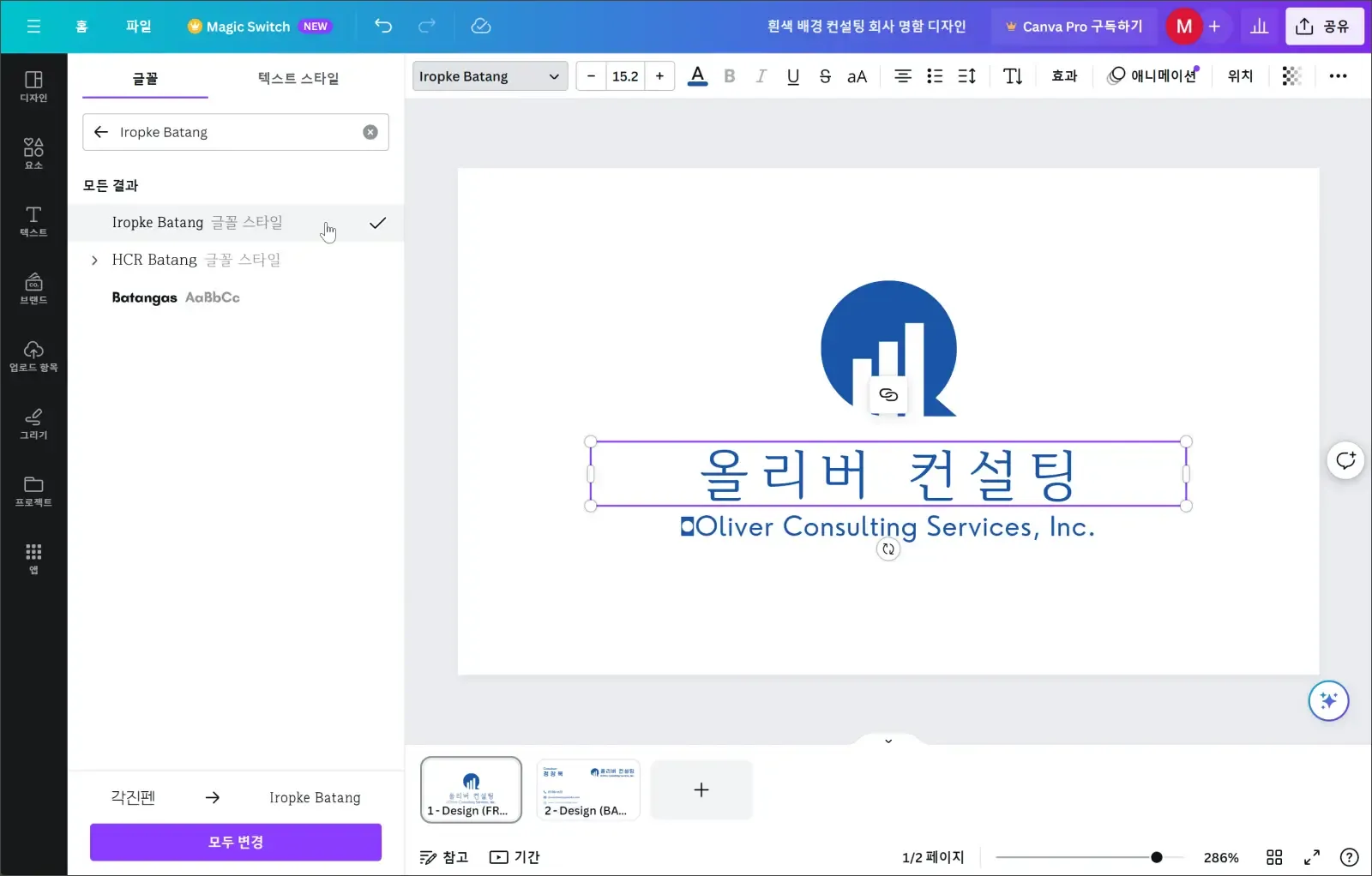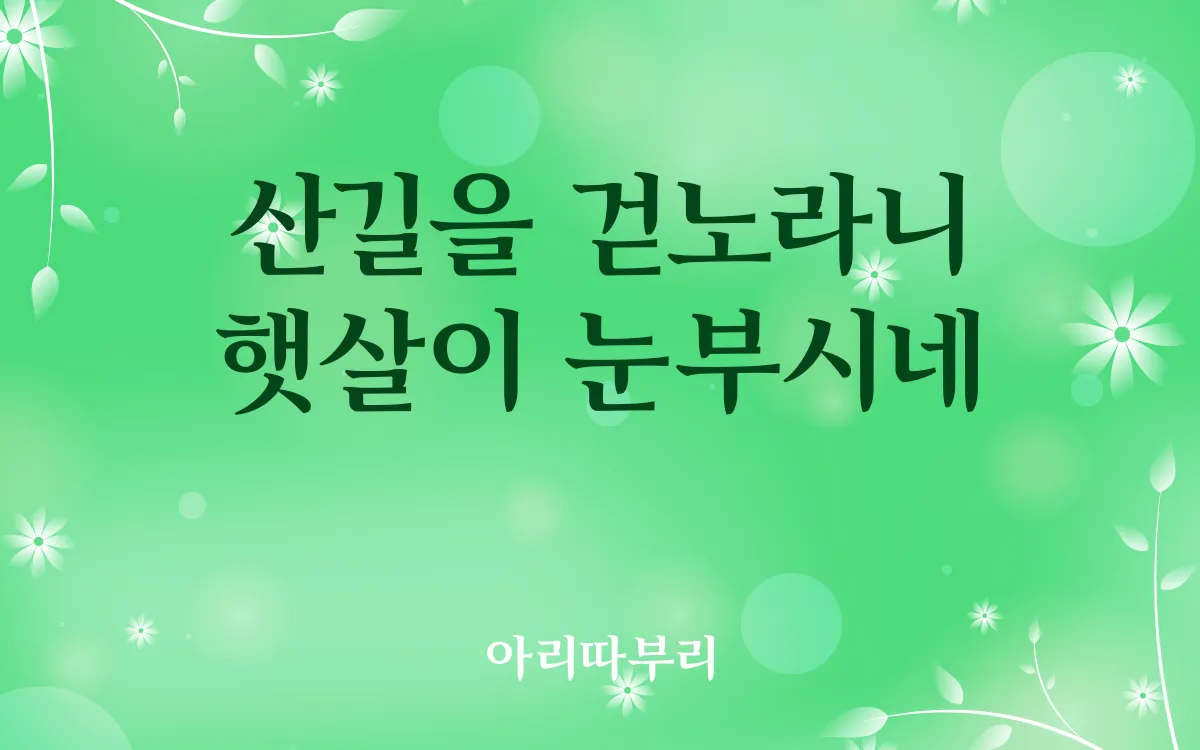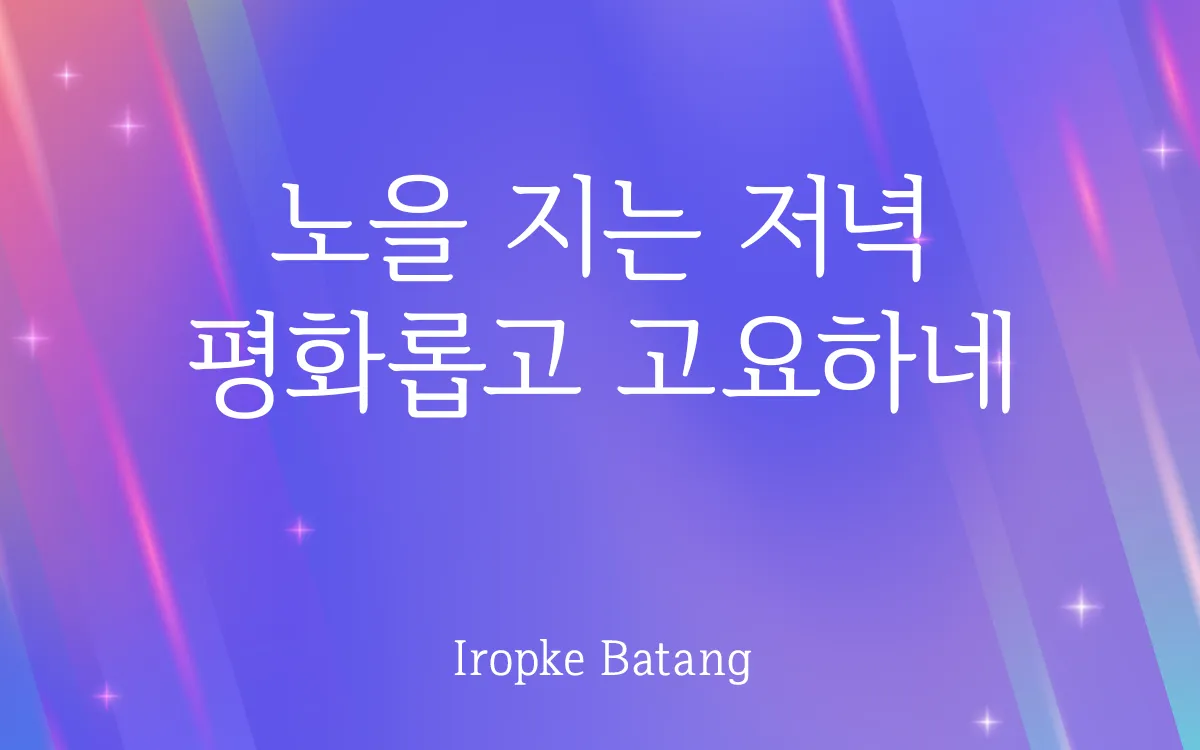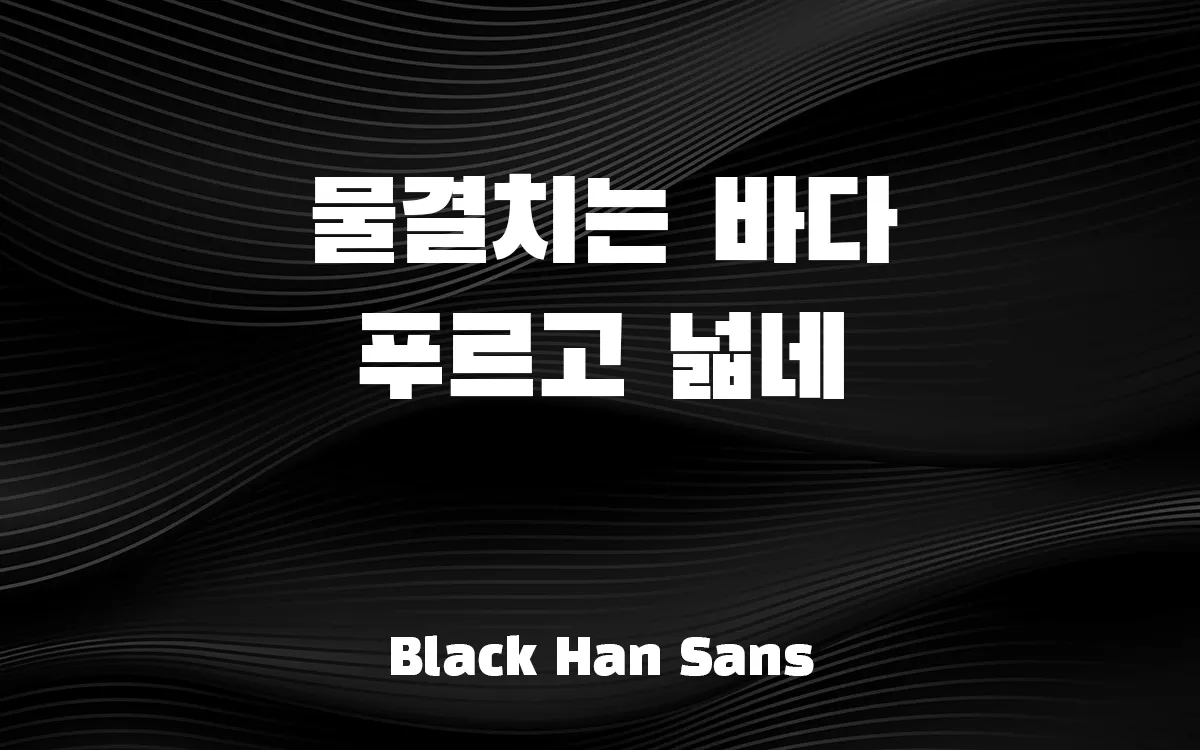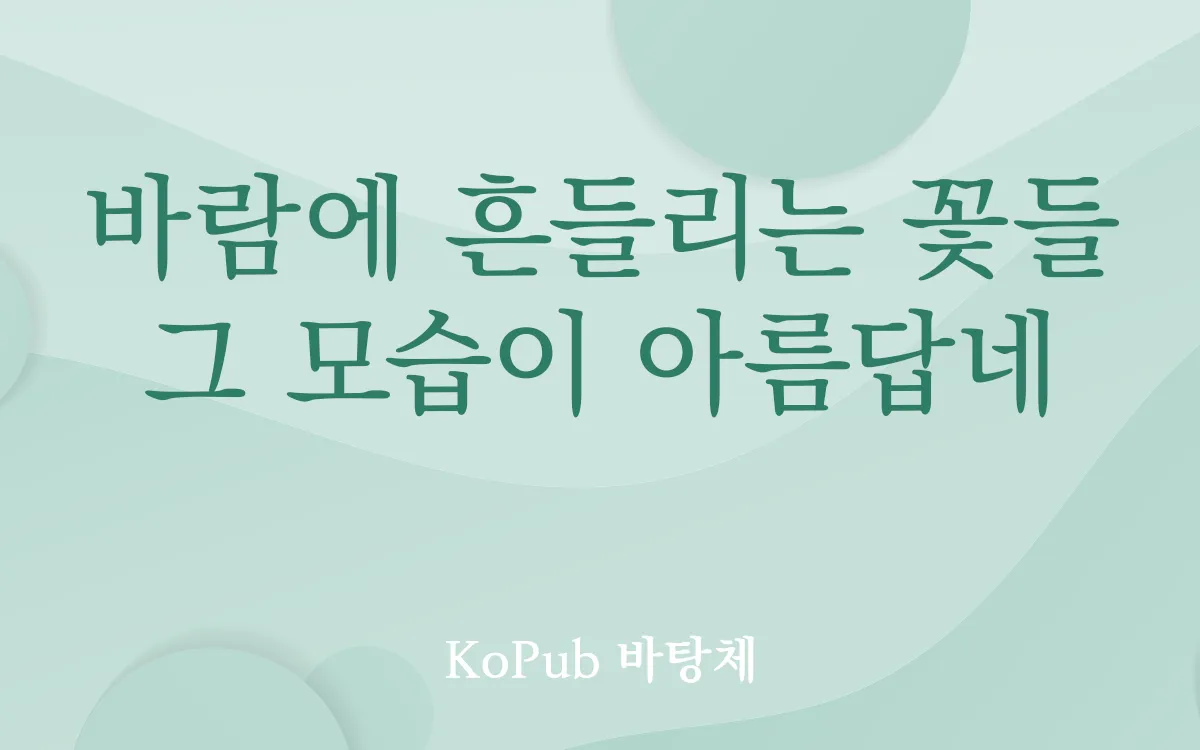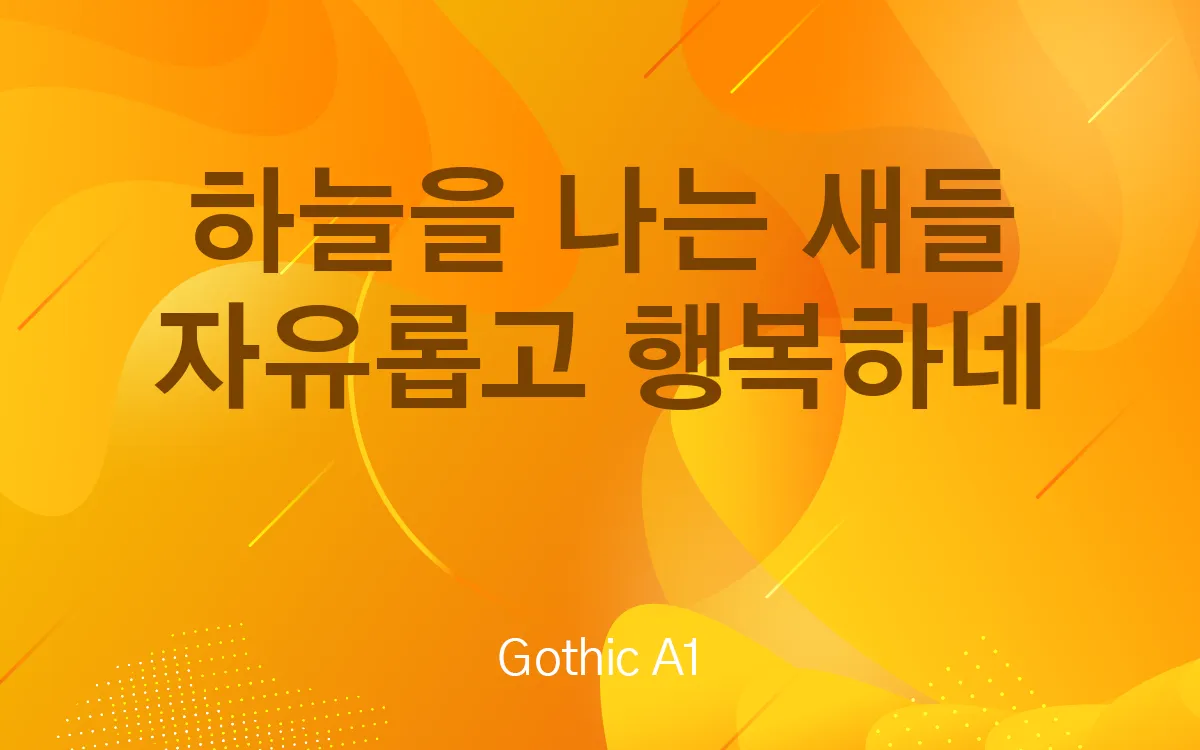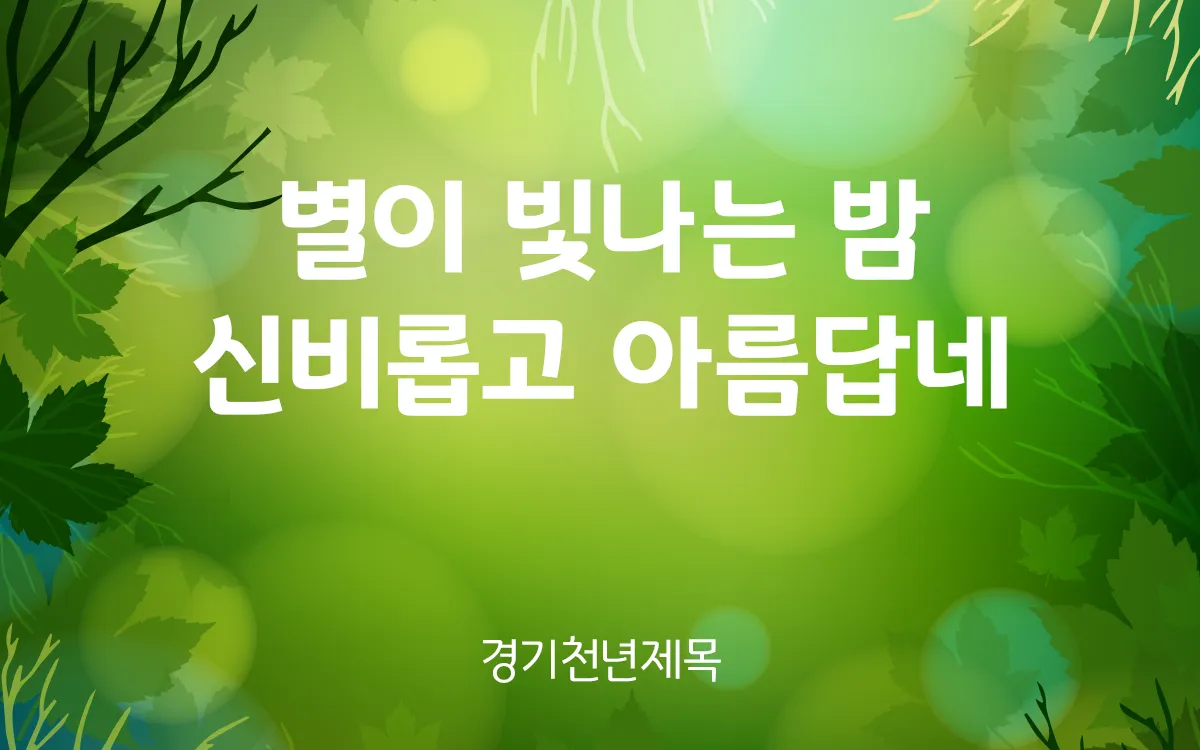
캔바(Canva)에서 사용하기 좋은 무료 한글폰트 6가지 추천
"캔바(Canva)에서 사용하기 좋은 무료 한글폰트 6가지 추천"
캔바(Canva)는 누구나 쉽게 디자인을 할 수 있는 온라인 디자인 플랫폼입니다.
다양한 템플릿과 이미지, 글꼴 등을 제공하여 디자인 경험이나 특별한 기술이 없어도 원하는 디자인을 만들 수 있습니다.
캔바(Canva)에서 사용하기 좋은 무료 한글폰트 6가지 추천
캔바(Canva)의 주요 기능
• 캔바에서는 다양한 템플릿을 제공하므로, 디자인 경험이 없는 초보자도 쉽게 원하는 디자인을 만들 수 있습니다.
• 텍스트, 이미지, 요소 등을 자유롭게 추가하여 원하는 디자인을 완성할 수 있습니다.
• 완성된 디자인은 다양한 형식으로 저장하거나 공유할 수 있습니다.
캔바에서 글꼴 바꾸는 방법
캔바 편집화면에서 상단의 폰트명을 선택하면 아래와 같이 글꼴을 검색할 수 있습니다.
경우에 따라 한글이 아닌 영어로 글꼴 이름을 입력해야 검색이 가능한 경우도 있습니다.
캔바에서 사용 가능한 무료 폰트 6가지 추천
캔바에서 바로 사용할 수 있는 상업적 이용이 가능한 무료폰트 6가지를 소개합니다.
아리따부리(Arita Buri)
아리따 글꼴은 아모레퍼시픽에서 제작한 폰트로 누구나 무료로 사용할 수 있는 나눔 글꼴입니다. 캔바에서 사용하기 위해서는 영어로 검색을 해야 합니다.
KoPub 바탕체
KoPub 글꼴은 한국출판인회의에서 제작한 글꼴로 사용등록을 하면 누구나 자유롭게 이용할 수 있는 무료 글꼴입니다.
고딕 A1(Gothic A1)
고딕 A1 글꼴은 구글이 배포하는 무료 글꼴로, 9가지의 두께를 자유롭게 사용할 수 있는 장점을 가지고 있습니다. 제목은 물론 본문용으로도 유용한 글꼴입니다.
검은 고딕(Black Han Sans)
ZESSTYPE에서 제작한 폰트로 구글을 통해 무료 배포되고 있습니다. 굵고 진한 한글 폰트를 원하시면 추천해 드릴 수 있는 무료 글꼴입니다.
이롭게 바탕(Iropke Batang)
(주)이롭게에서 제작하여 배포하는 글꼴로 모든 한글을 표현할 수 있는 11,172자를 모두 지원하는 글꼴입니다. 상업적으로도 자유롭게 사용이 가능합니다. 캔바에서 사용하기 위해서는 영어로 검색을 해야 합니다.
경기천년제목
경기도에서 제작한 경기도 서체는 경기도의 정체성을 강화할 목적으로 제작되었습니다. 경기천년제목체와 경기천년바탕체로 구성되어 있으며, 허가절차 없이 누구나 자유롭게 사용할 수 있습니다.